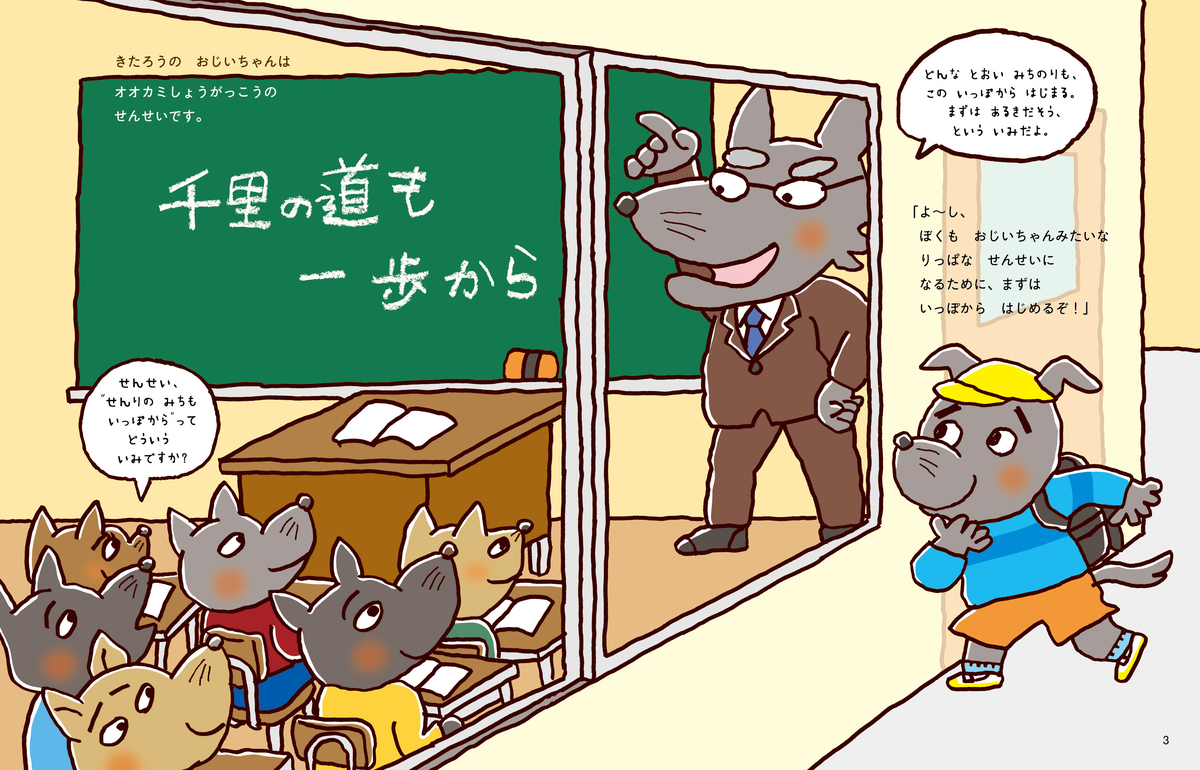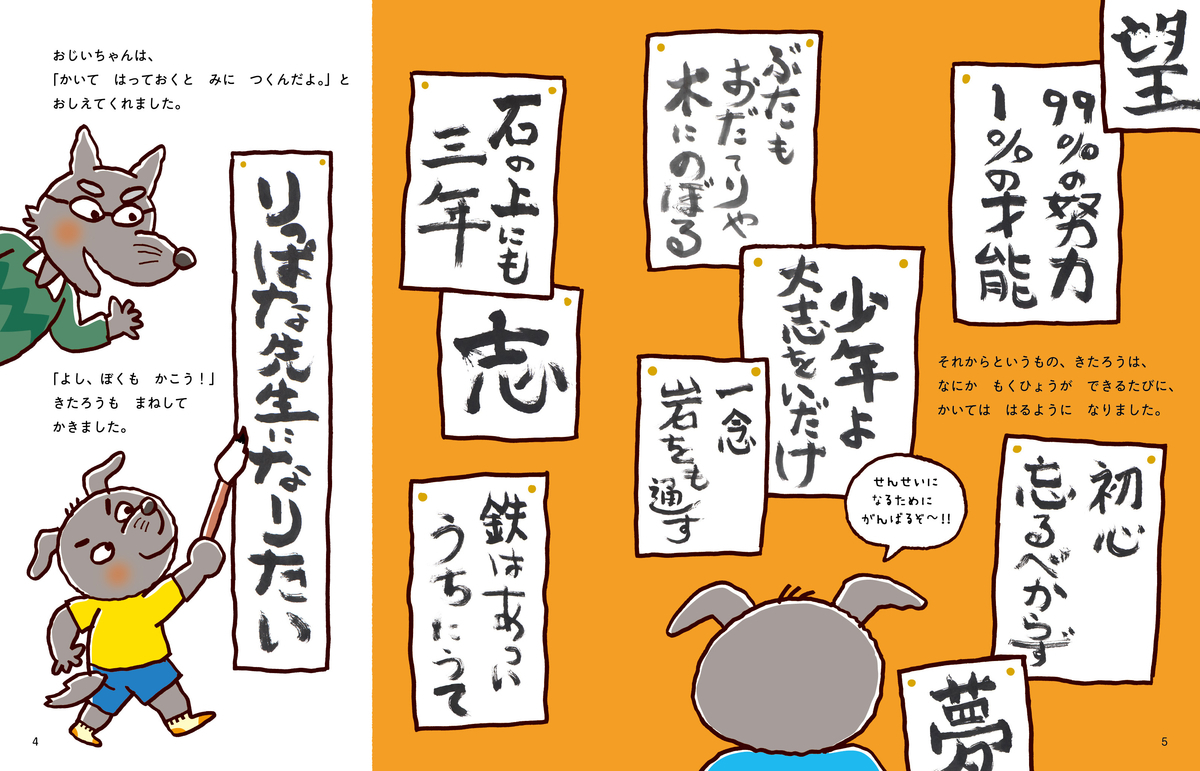
おおかみせんせい はじめてのしょうがっこう
学研ホールディングスのグループ会社である学研プラスは、数々のヒット作を世に送り出している人気絵本作家きむらゆういち氏作絵の最新作絵本「おおかみせんせい はじめてのしょうがっこう」を2020年2月6日に発売した。
絵本界の人気作家3人が夢のコラボ「おおかみせんせい はじめてのしょうがっこう」
「おおかみせんせい はじめてのしょうがっこう」は、絵本界の人気作家3名による夢のコラボが実現した作品。作と線画は『あらしのよるに』のきむらゆういち氏、彩色は『あかまるどれかな?』のしみずだいすけ氏、デザインとアートディレクションは『しましまぐるぐる』のかしわらあきお氏という3名のコラボによって、楽しいストーリー&POPな絵とデザインが実現。
また、きむらゆういち氏が絵を描くように描いた「書」がストーリーの中の随所に登場する。味のある「書」はまるで絵のようで「僕も」「私も」「書いてみたい」と思わせる。そんな気持ちをさらに大きくかきたてるような工夫として、主人公・きたろうの原寸大の書「夢」を、巻末にとじ込みで掲載している。きたろうは心の動きをすぐに書で表すため、読んでいる子どもたちも、絵本を読んだあとに、きっと、何かを感じて「描いてみよう」「書いてみよう」と思うに違いない。
格言やことわざの楽しさも学べる「おおかみせんせい はじめてのしょうがっこう」
「おおかみせんせい はじめてのしょうがっこう」は「将来の目標や夢を文字や絵で描いてみよう、きっとかなうよ」というコンセプトで作られている。きたろうが教師を目指す経緯や学校生活の中で思ったことを表した様々な格言や名言、ことわざが、漢字も交えて登場する。巻末には「おおかみせんせい書の解説コーナー」として、ことわざや格言を解説。年齢の低い読者には「難しい」と感じるかもしれないが、学研らしい学習コーナーで、知らなかった格言やことわざを学ぶことができるよう、工夫を鉾度されている。
ストーリーは、夢に向かってつきすすむ大切さ、一途さと、オオカミとしての食欲を抑え、「教育に動物の種類は関係ない!」と頑張るきたろうの忍耐と葛藤をコミカルに描いており、きむらゆういち氏らしい、笑いのつぼもたくさん入っている。特に、国語の時間に例文でついつい本音を書いてしまったきたろうの、赤字に注目。
▼オオカミのきたろうは、小さいころからおじいちゃんのような立派な先生になりたいと、教師を志す
▼「書」にして書いて貼るとみにつくんだよ、とおじいちゃんに教わり、いつしか夢や目標を筆で書くのが習慣となったきたろう。猛勉強の結果、試験に合格、あこがれた先生になれたのだが…。
▼コブタ小学校の1年生の担任になってしまい、無邪気にくっつかれて困惑のきたろう先生。実は豚肉は大好物なのだ。